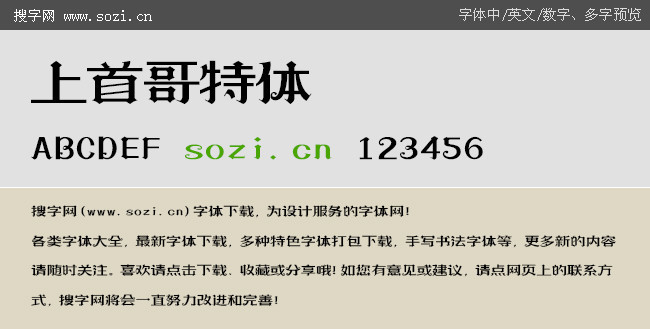
上首哥特體
搜字網(wǎng)給大家提供一款上首哥特體中文字體下載,上首哥特體字體筆畫與筆畫之間運(yùn)用了菱形和圓勾,裝飾性很強(qiáng),線條的粗細(xì)變化也是這套字體的一大特色,給字體整體呈現(xiàn)出哥特風(fēng)格?蓱(yīng)用于各類報(bào)紙、雜志、海報(bào)、包裝等廣告設(shè)計(jì)。